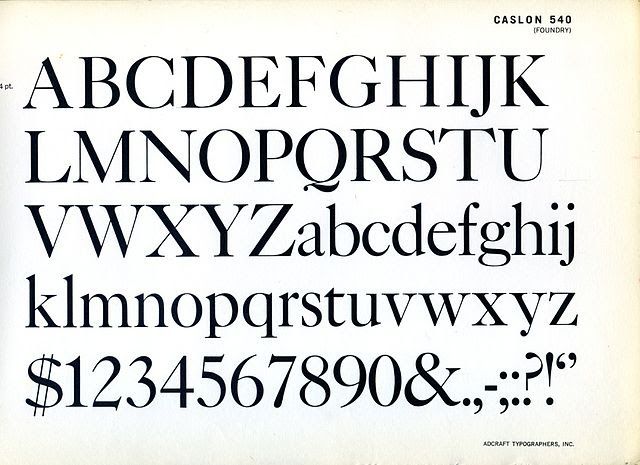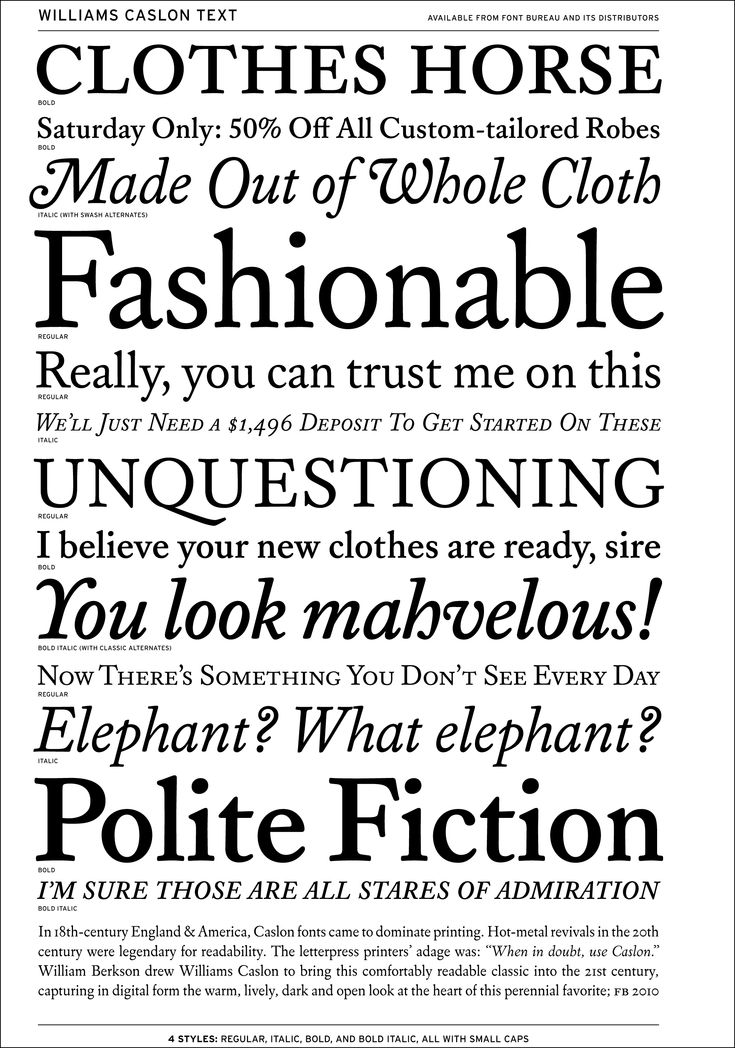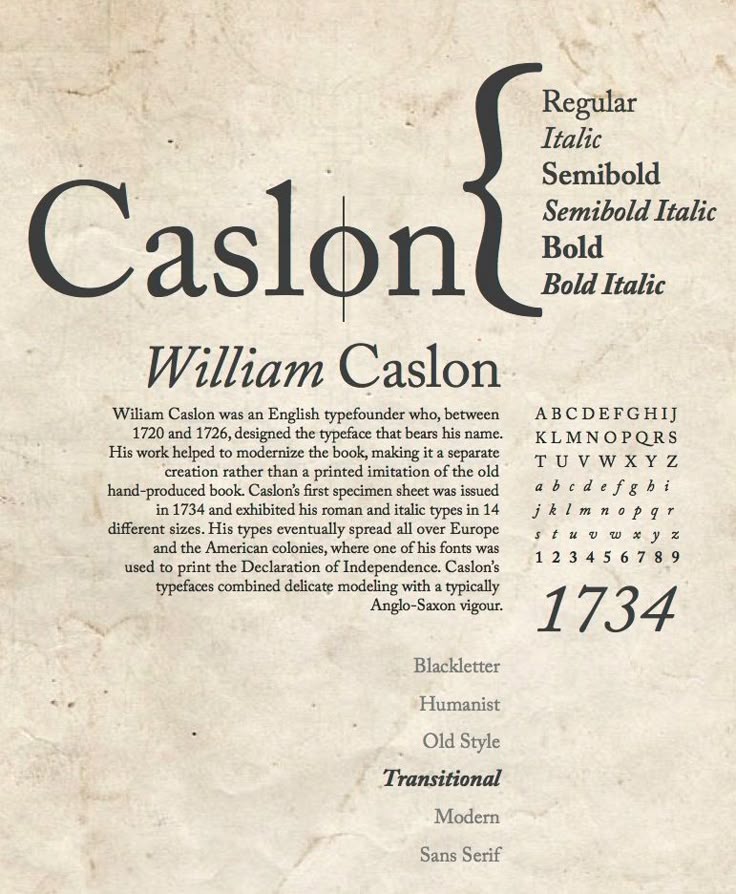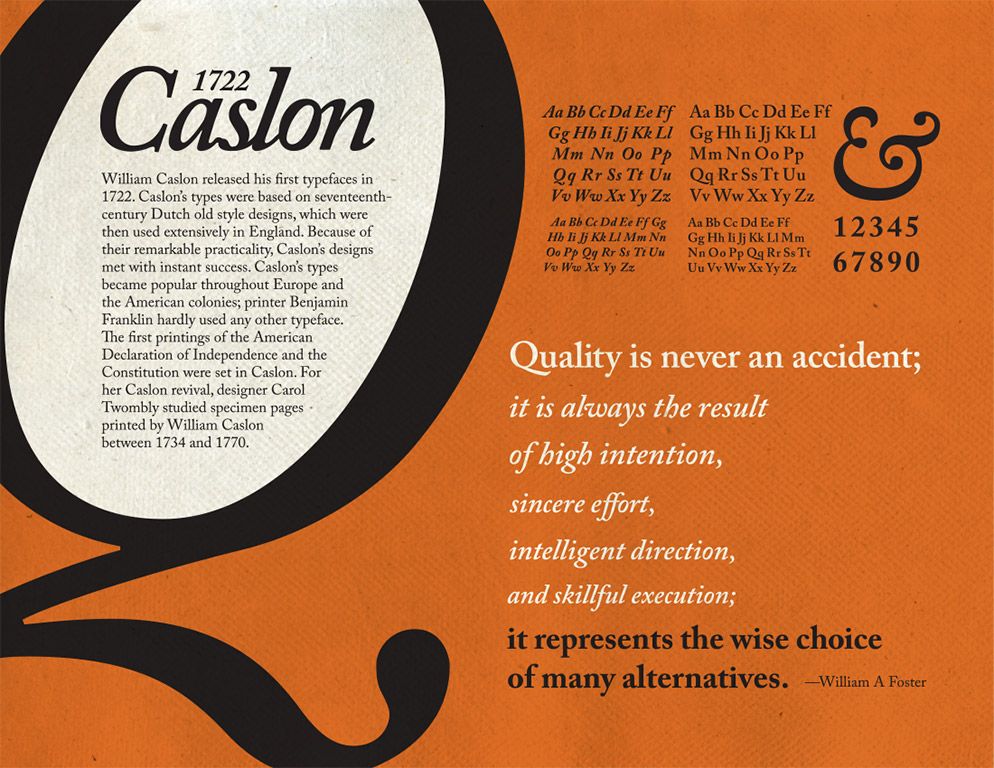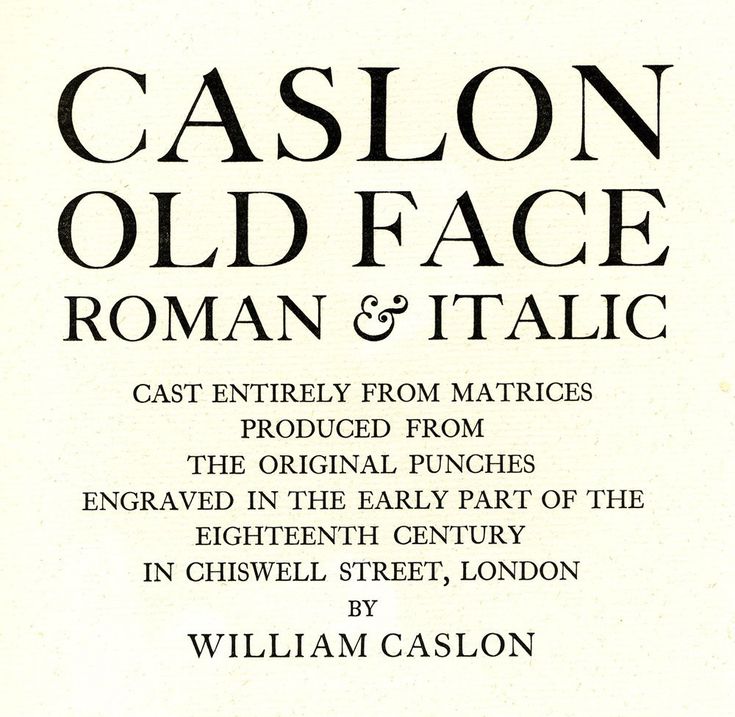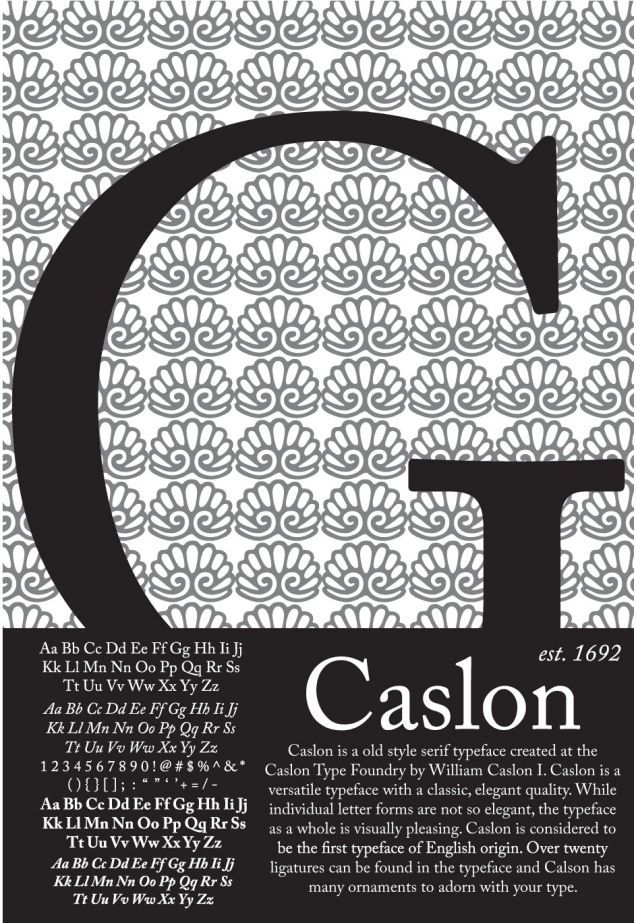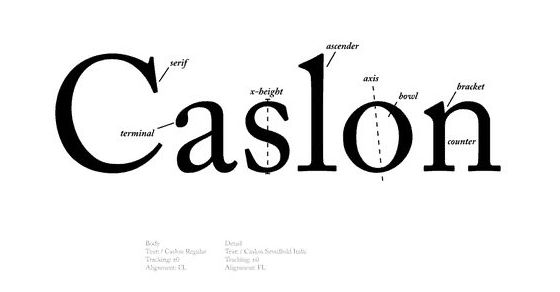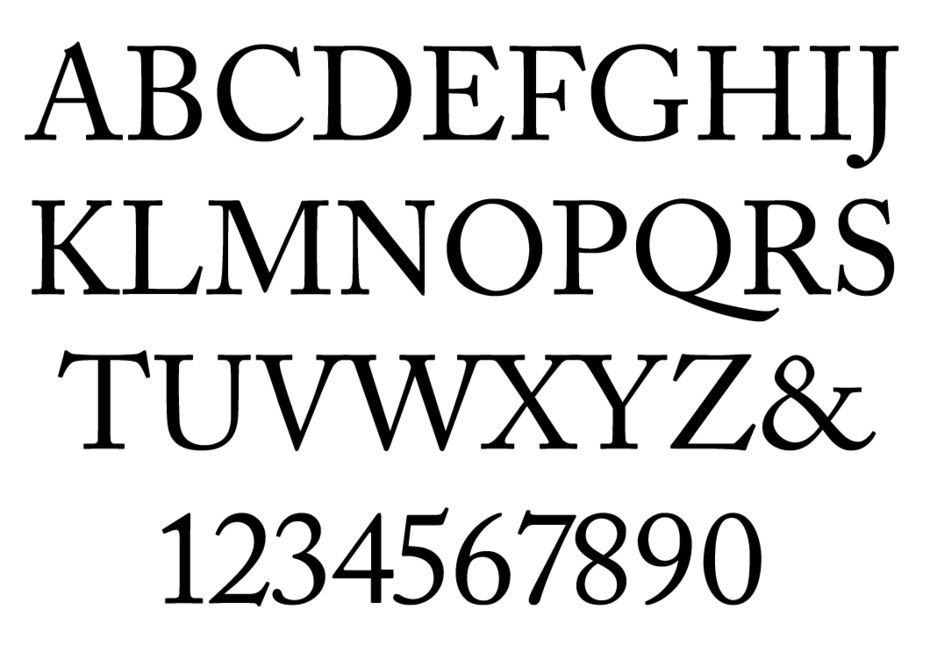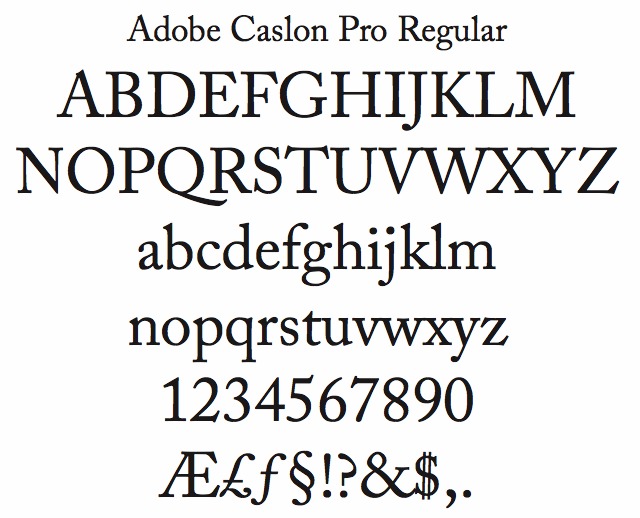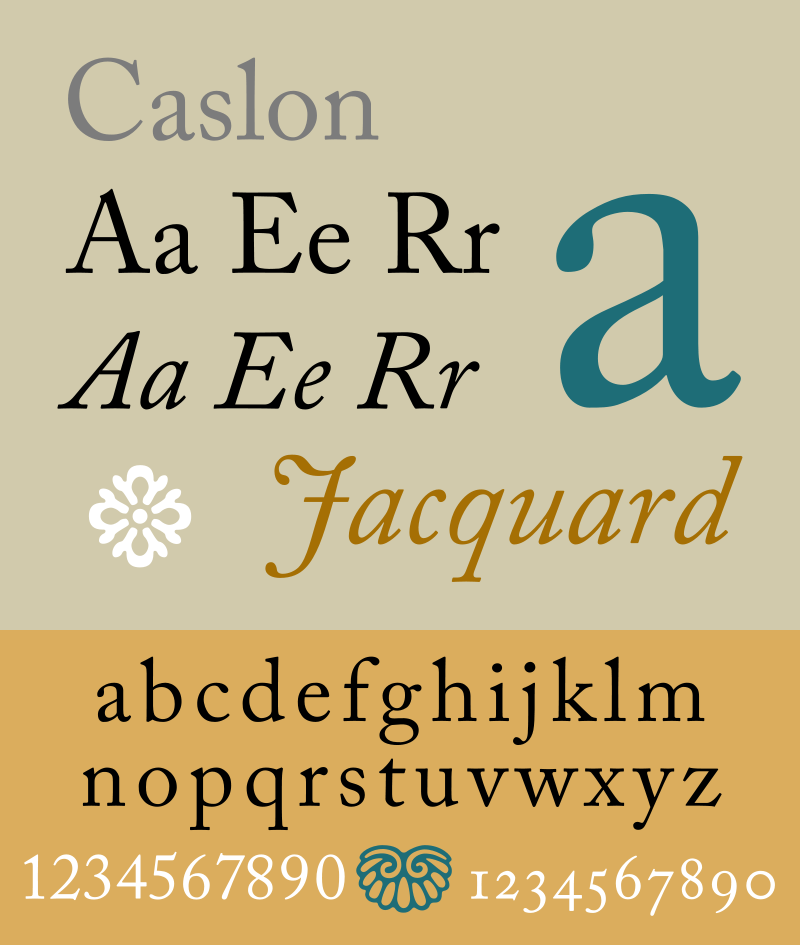
Уильям Кэзлон-
старший
[1] Уильям Кэзлон I (старший) (William Caslon 1,1692-1766).
Английский гравер, пуансонист и словолитчик, автор английской
антиквы старого стиля (1725). В 1720 г. основал в Лондоне семейную
фирму, которая существовала под названием Caslon до 1937 г.,
вначале на Ironmonger Row, а с 1737 г. на Chiswell Street. С 1734
по 1740 гг. выпустил 8 изданий первого каталога шрифтов с 38
шрифтами, из которых 35 работы Кэзлона. В 1742 г. издан второй
каталог, где помещены 48 его шрифтов и И шрифтов работы его
сына, Уильяма Кэзлона II. В 1748,1749,1763 и 1764 гг. выпускал
каталоги шрифтов совместно с сыном. Кроме латинских антиквы
и курсива, в этих каталогах помещены текстура, саксонские,
греческие, еврейские, сирийский, арабский, готский, армянский,
эфиопский, самаритянский, коптский шрифты, а также орнаменты.
С1763 г. шрифтовые каталоги Кэзлона издаются в форме книг, а не
листов с образцами набора, как ранее.
[3] Уильям Боуэр-старший (William Bower the elder, 1663-1737).
Лондонский издатель, друг и кредитор Уильяма Кэзлона.
[5] Джозеф Джексон (Joseph Jackson, 1733-1792). Лондонский
пуансонист и словолитчик, ученик Уильяма Кэзлона. В1763 г.
открыл собственную словолитню, которая в 1795 году была куплена
Уильямом Кэзлоном III.
[6] Томас Коттрелл (Thomas Cottrell, ум. в 1785). Лондонский
пуансонист и словолитчик, ученик Уильяма Кэзлона, учитель
Роберта Торна (Robert Thorne, 1754-1820). Котрелл изготовил
первые плакатные шрифты в кегле 144 пункта (Twelve Lines Pica)
ок. 1765 r.
[7) Кристоффел ван Дейк (Christoffel van Dijck/van Dyck,1601-1669).
Голландский пуансонист и словолитчик немецкого происхождения.
Работал в Амстердаме. Шрифты его работы, известные по изданиям
Эльзевиров, считаются лучшими представителями голландской
антиквы старого стиля.
[8]
[9]
Бенджамин Франклин [10]
Дирк Воскенс (Dirk Voskens, ум. в 1691). Голландский пуансонист
и словолитчик конца XVII века, учитель Николая Киша (Nicholas
Kis/Tótfalusi Kis Miklós, 1650-1702). Работал в Амстердаме.
Бенджамин Франклин (Benjamin Franklin, 1706-1790).
Американский просветитель, государственный деятель, учёный
и типограф. Один из авторов Декларации независимости США
(1776) и американской Конституции (1787).
[И] Дэниэл Беркли Апдайк (Daniel Berkeley Updike, 1860-1941).
Американский издатель, типограф и историк типографики,
владелец издательства Merrymount Press, которое он основал в 1894
г. в Бостоне. Его классическое исследование истории шрифтов
“Printing types. Their history, forms, and use” Harvard University
Press/Cambridge, Massachusetts, 1922,1937,1951, New Castle/
London, 2001 основано на его лекциях в Гарвардском университете
в 1910-16 гг.
Антиква
Дэниэл Беркли
Апдайк
Кэзлон
Уильям Кэзлон (Англия)
1725
Английская антиква старого стиля
[12] Уильям Кэзлон II (William Caslon II, 1720—1778), сын Уильяма
Кэзлона I. Английский словолитчик. Работал в Лондоне, возглавлял
фирму William Caslon с 1742 по 1778 г.
[13] Уильям Кэзлон III (William Caslon III, 1754-1833), сын Уильяма
Кэзлона И, внук Уильяма Кэзлона старшего. Английский
словолитчик. Работал в Лондоне с 1792 по 1807 г.
[14] Уильям Кэзлон IV (William Caslon IV, 1780-1869), сын Уильяма
Кэзлона III, правнук Уильяма Кэзлона старшего.
Английский
словолитчик. Работал в Лондоне, возглавлял фирму William Caslon
с 1807 по 1819 г., после чего она была куплена фирмой Blake, Garnett
& Со. В его каталоге в 1816 г. был опубликован первый известный
шрифт без засечек—гротеск Two Line English Egyptian.
[15] Лоренс Джонсон (Laurence Johnson, 1801-1860). Американский
словолитчик. Работал в Филадельфии. Выпустил в 1858 г, прямой
и курсивный шрифт Caslon под названием Old Style No.l, который
в 1892 г. попал в шрифтовую библиотеку American Typefounders
(ÄTF) и был назван ÄTF Caslon 471.